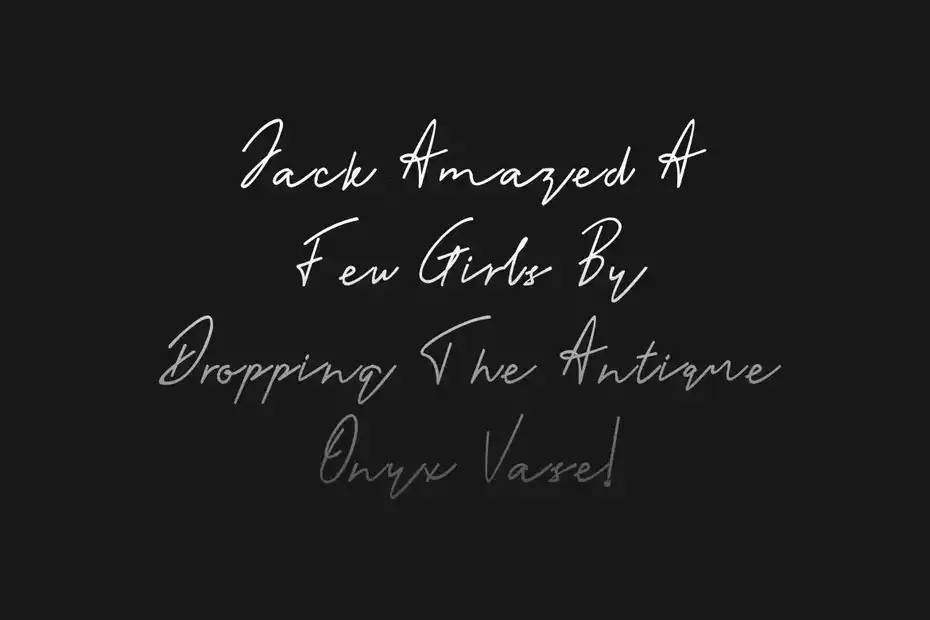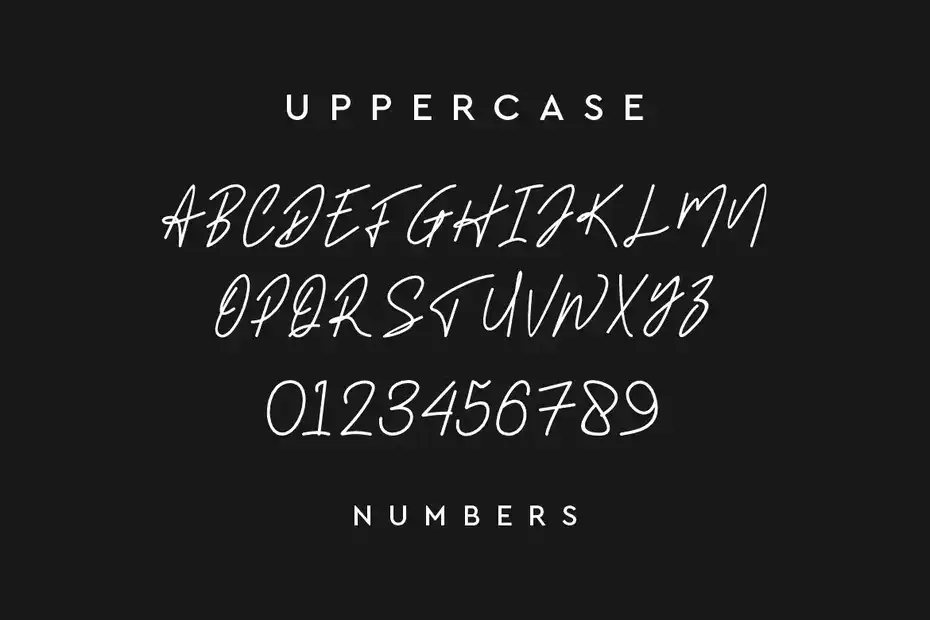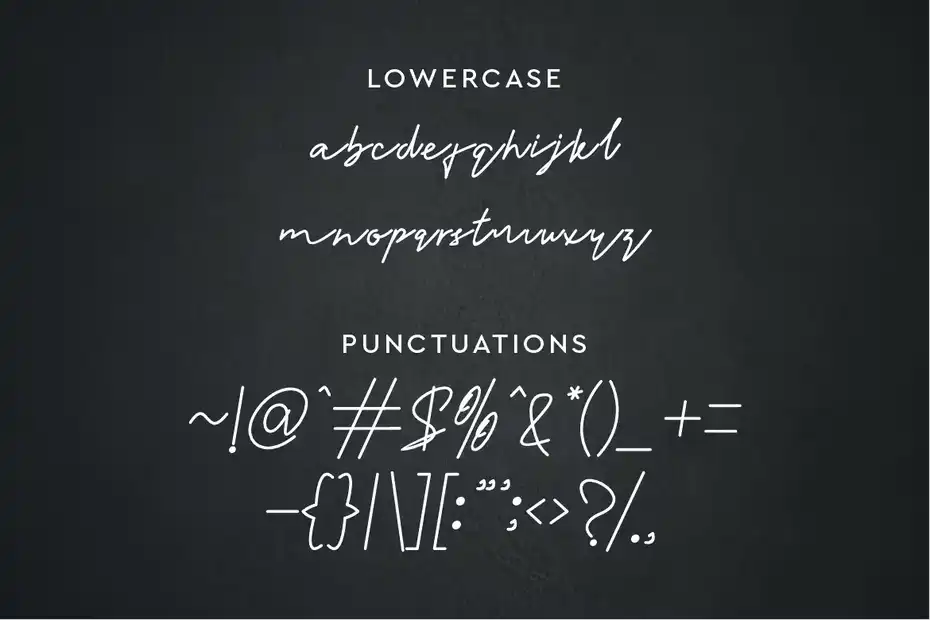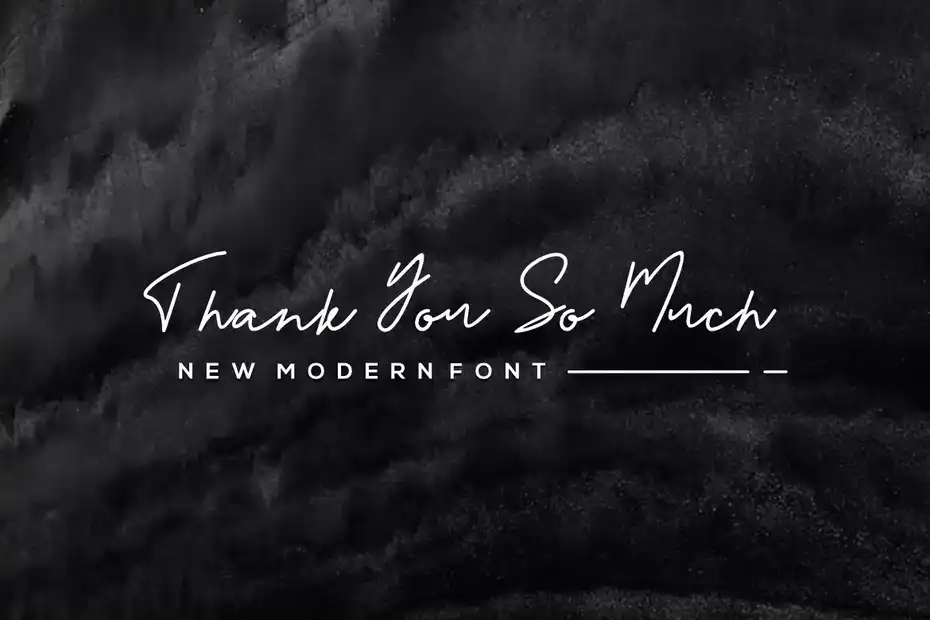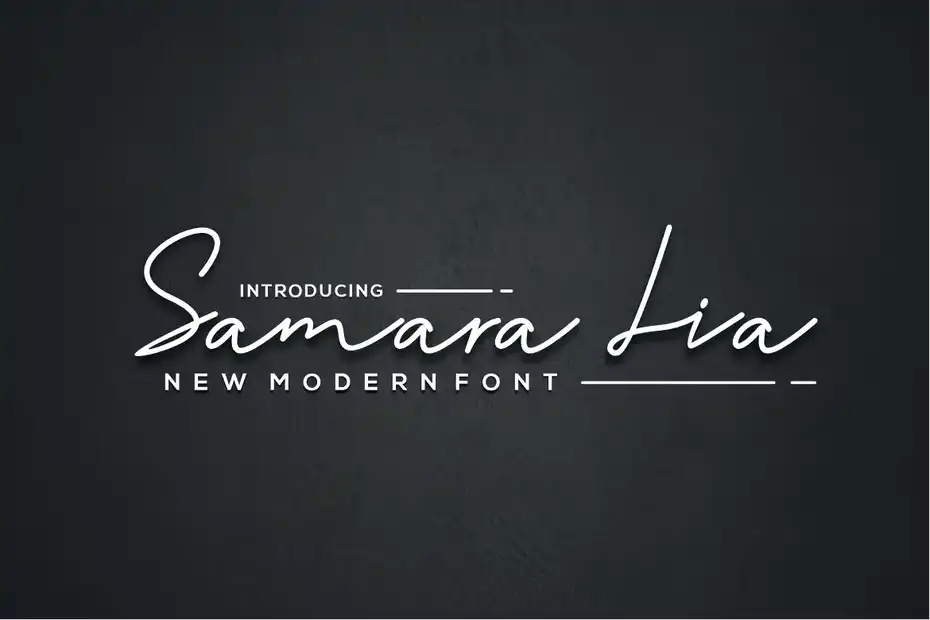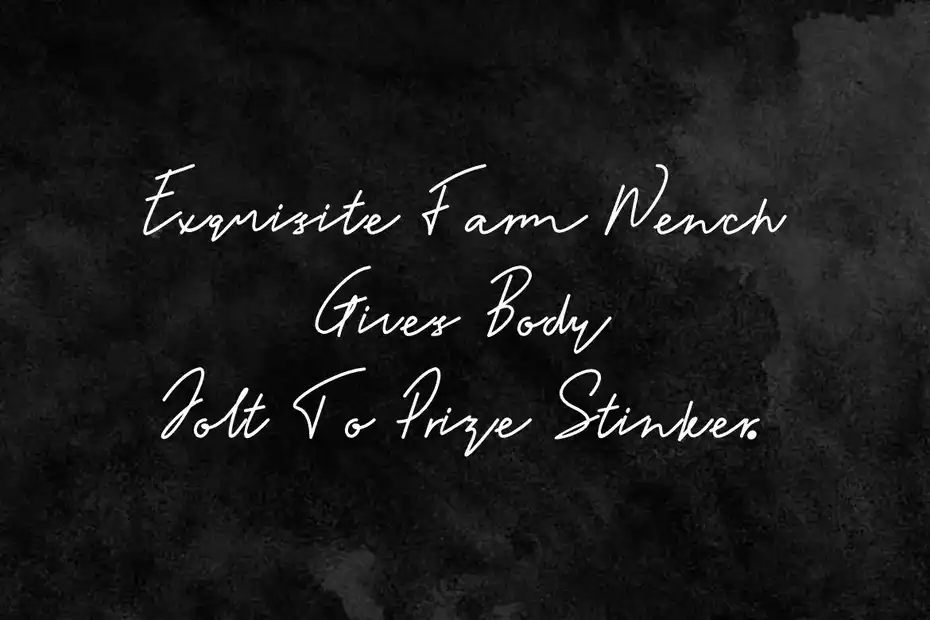
فونت انگلیسی Samara lia font : این مجموعه شامل یک فونت دست نویس است که برای لوگو، امضا، برندینگ، کارت عروسی، نقل قول‌ های تایپوگرافی، جلد مجله یا کتاب، سربرگ وب‌ سایت، لباس، طراحی بسته‌ بندی و غیره مناسب میباشد.
• فضا بین حروف: معمولی، متراکم